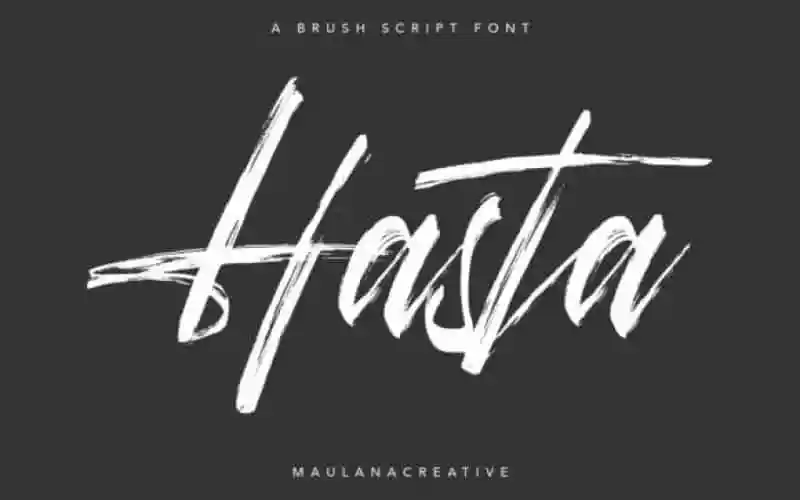
Hasta Brush Script Font – Download Grátis
A Hasta Brush Script Font é uma fonte elegante e amigável feita à mão usando técnica de tinta-pincel seca. Sua estilização natural e única a torna ideial para diversos projetos gráficos, desde logotipos até capas de livros e materiais promocionais. Fabricada pelo designer Maulana Creative, essa fonte foi criada utilizando técnicas manuais que resultam em textura de pincel natural, perfeitamente adaptável às áreas como revistas, identidade de marca, promoção, embalagens e muito mais. Com a Hasta Brush, você pode conferir um toque autêntico ao seu trabalho gráfico. A fonte é especialmente adequada para uso em assinaturas, materiais de embalagem, logotipos, citações tipográficas, capas de revistas ou livros, cabeçalhos de websites e até mesmo na confecção de roupas ou embalagens. Sua versatilidade é impressionante, permitindo aplicação em um vasto leque de produtos que exigem um toque cuidadosamente personalizado.